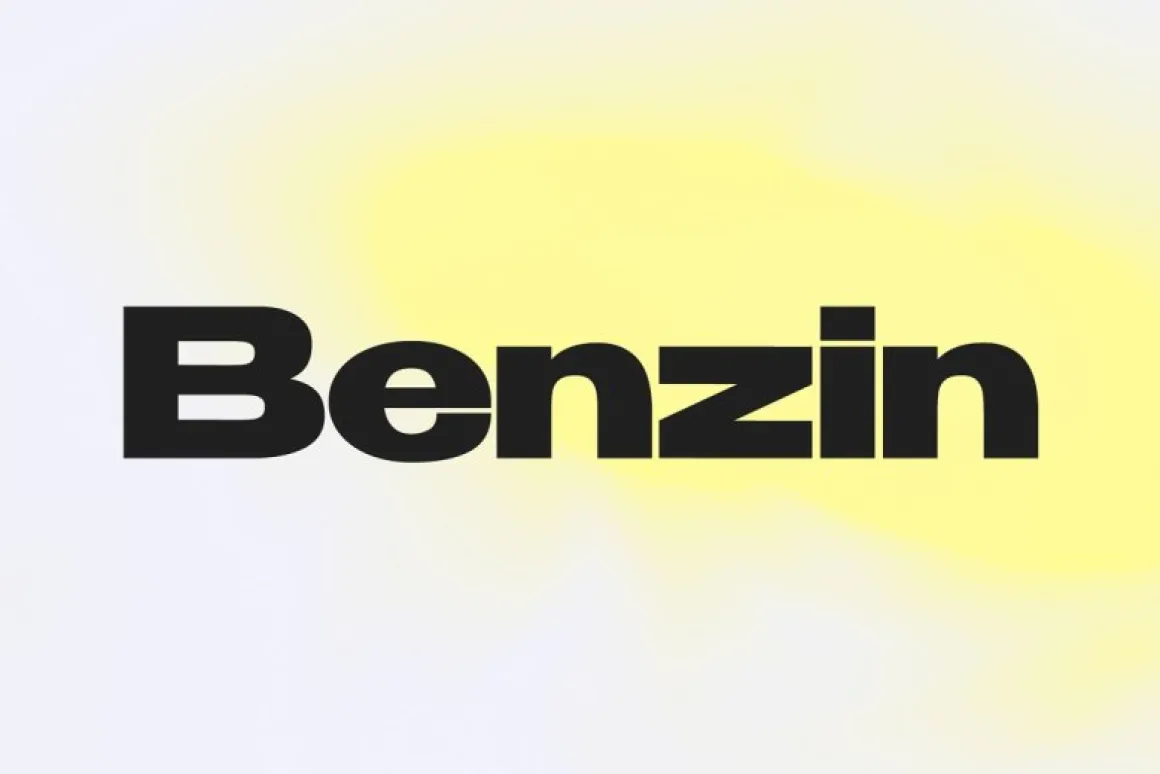
Designer tìm phông chữ hiện đại thường gặp lỗi font Benzin bị thiếu dấu tiếng Việt hoặc đường nét bị nhòe khi in trên các sản phẩm bao bì công nghệ. Những sai sót này khiến thiết kế mất đi sự đồng nhất, làm giảm tính chuyên nghiệp của bộ nhận diện thương hiệu.
Font Benzin là gì?
Benzin là một bộ phông chữ thuộc dòng Sans-serif hiện đại, gây ấn tượng nhờ cấu trúc hình học tối giản và các đường vát góc tinh tế. Benzin font family mang lại cảm giác vững chãi, uy lực nhưng vẫn giữ được sự tinh tế cần thiết cho các ấn phẩm truyền thông đương đại. Đây là lựa chọn thường xuyên cho thiết kế logo công ty công nghệ, ô tô, điện tử hoặc các tiêu đề hồ sơ năng lực yêu cầu sự mạnh mẽ và hiện đại.
Hệ gia đình phông chữ này cung cấp đầy đủ các biến thể từ nét mảnh đến Benzin Bold font cực đậm. Bản việt hóa tại In Viva đã được hiệu chỉnh bảng mã Unicode chuẩn, giúp designer gõ tiếng Việt ổn định mà không làm mất đi các góc vát đặc trưng của bộ chữ. Việc sử dụng phông chữ này giúp các sản phẩm in ấn quà tặng của doanh nghiệp bạn toát lên vẻ ngoài sang trọng, bắt kịp xu hướng thiết kế tối giản toàn cầu.
Lưu ý: Khi bạn thực hiện thiết kế bằng Benzin font family, hãy chú ý khoảng cách ký tự (Tracking) để các mảng khối của chữ không bị dính nét sau khi thực hiện gia công nhiệt.
5 ứng dụng của font Benzin trong thiết kế và in ấn
Vẻ đẹp mạnh mẽ và hiện đại của Benzin giúp các sản phẩm bao bì, quà tặng doanh nghiệp trở nên nổi bật hơn khi kết hợp cùng các kỹ thuật in ấn và gia công phù hợp:
- Thiết kế bao bì hộp quà công nghệ: Benzin phù hợp để thể hiện tên thương hiệu, tên sản phẩm trên hộp cứng đựng sạc dự phòng, tai nghe hoặc phụ kiện điện tử nhờ cấu trúc chữ mang phong cách kỹ thuật, hiện đại.
- Sản xuất set quà tặng văn phòng in logo: Logo sử dụng font Benzin khi in UV trên bình giữ nhiệt kim loại, sạc dự phòng hoặc phụ kiện công nghệ giúp sản phẩm có điểm nhấn cá tính, phù hợp với các dòng quà tặng doanh nghiệp.
- In ấn túi giấy thương hiệu hiện đại: Sử dụng Benzin cho logo, slogan hoặc thông tin nhận diện trên túi giấy Ivory, giấy mỹ thuật giúp thương hiệu thể hiện phong cách chuyên nghiệp, tối giản.
- Trang trí bảng biển và không gian showroom: Với định dạng vector, font Benzin có thể ứng dụng trong thiết kế bảng hiệu, backdrop hoặc khu vực trưng bày, giúp hình ảnh thương hiệu duy trì sự đồng nhất trong không gian.
- Sản xuất tem nhãn decal sản phẩm: Các biến thể đậm như Benzin Bold phù hợp để thể hiện tên sản phẩm, mã sản phẩm hoặc thông tin ngắn trên tem nhãn, giúp nội dung dễ nhận diện hơn khi in trên nhiều chất liệu.
4 lưu ý khi sử dụng font Benzin việt hóa
Để font Benzin giữ được hình dáng rõ nét khi đưa vào sản xuất thực tế, designer cần chú ý các yếu tố kỹ thuật sau:
- Lựa chọn độ dày nét chữ phù hợp: Benzin có nhiều biến thể độ dày khác nhau. Khi sử dụng cho tem nhãn hoặc nội dung kích thước nhỏ, nên ưu tiên các phiên bản Medium hoặc Bold để hạn chế tình trạng mất nét khi in trên giấy có độ hút mực cao.
- Tối ưu đường Path cho gia công bế nổi: Khi sử dụng Benzin làm logo trên hộp quà, file vector cần được xử lý các điểm neo và góc chữ phù hợp. Việc tối ưu đường path giúp khuôn dập thể hiện rõ chi tiết chữ, hạn chế ảnh hưởng đến phần giấy trong quá trình gia công.
- Kiểm tra hệ màu CMYK trước khi in: Với các thiết kế sử dụng font chữ tối giản, màu sắc của logo và tiêu đề cần được kiểm tra trước khi sản xuất để hạn chế sự khác biệt giữa file thiết kế và thành phẩm.
- Convert font trước khi gửi xưởng: Trước khi xuất file sản xuất, designer nên thực hiện Create Outlines để chuyển đổi nội dung chữ thành vector, giúp hạn chế lỗi thiếu font hoặc sai kiểu chữ khi mở file trên hệ thống khác.